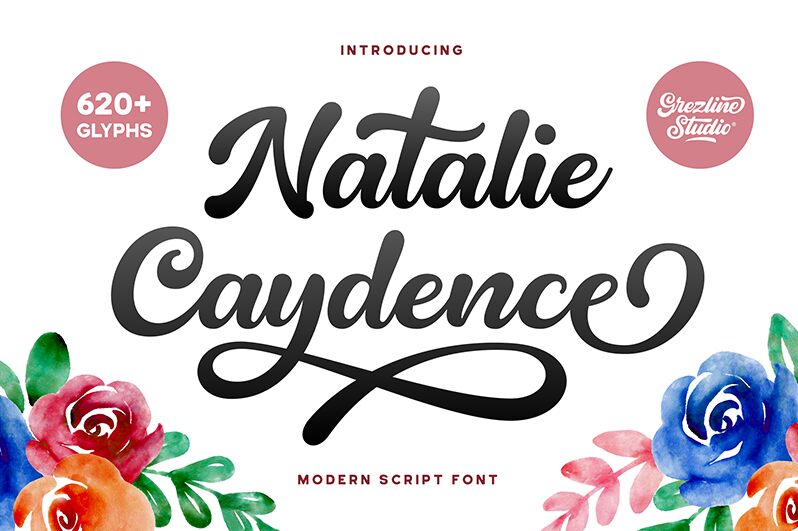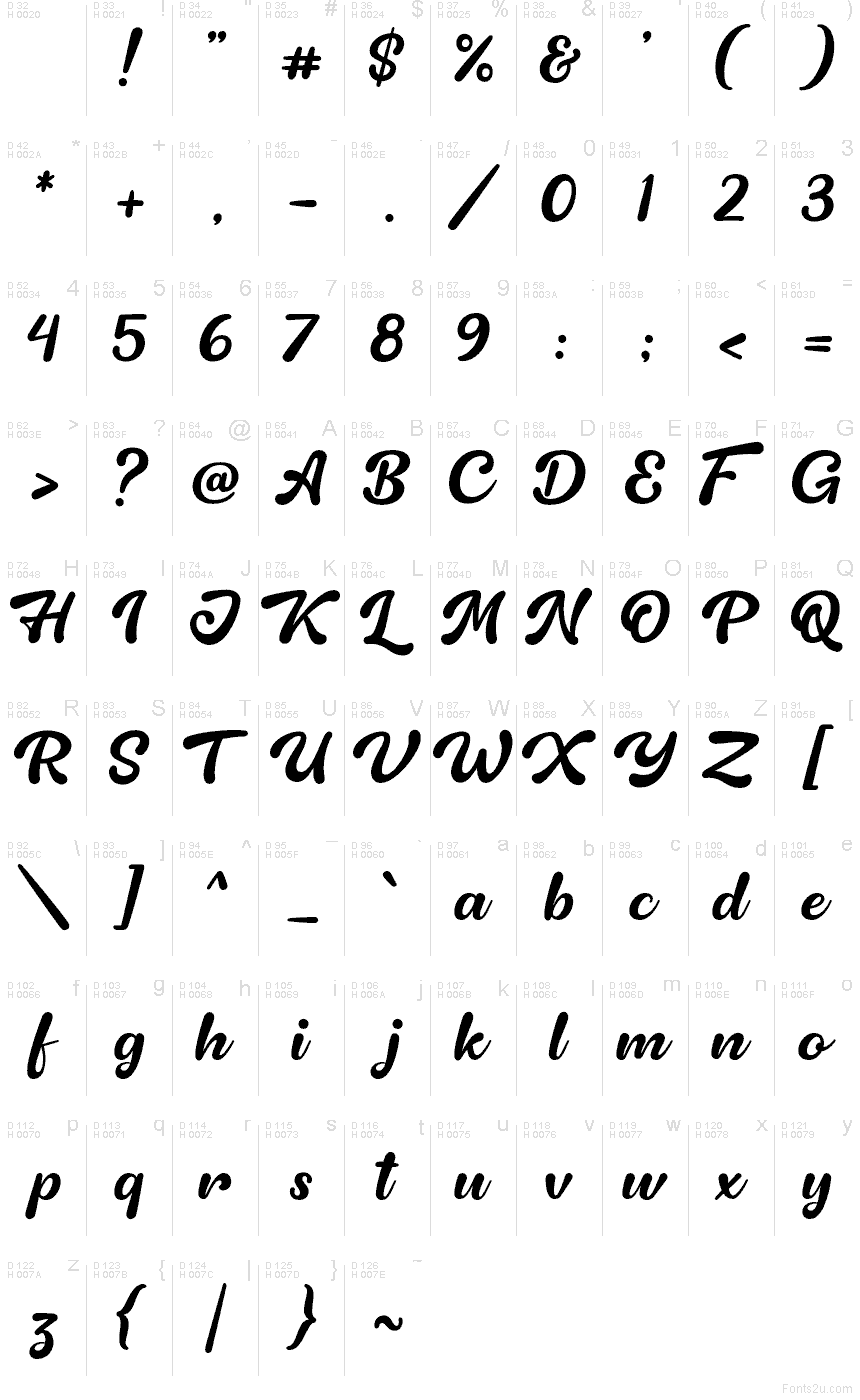
Natalie Caydence, gestaltet von Akhmad Reza Fauzi, ist eine kostenlose kalligrafische Schreibschrift mit breiten, schwungvollen Versalien, großzügigen Schlaufen und kompakten Verbindungsstrichen, die einen lebendigen Fluss im Stil einer Signatur erzeugen. Wechselnde Strichstärken und ausgeprägte Kurven halten das Schriftbild dynamisch.
Ihre fließende Bewegung harmoniert mit Themen aus Romantik und Mode, sodass sie sich für Hochzeitseinladungen, Kosmetikverpackungen, Boutique-Branding und Mode-Editorials eignet. Ihr naheliegendster Einsatzbereich ist die Hochzeitspapeterie, da die übergroßen Versalien als dekorative Zierelemente für Namen, Monogramme und Details der Zeremonie dienen können.